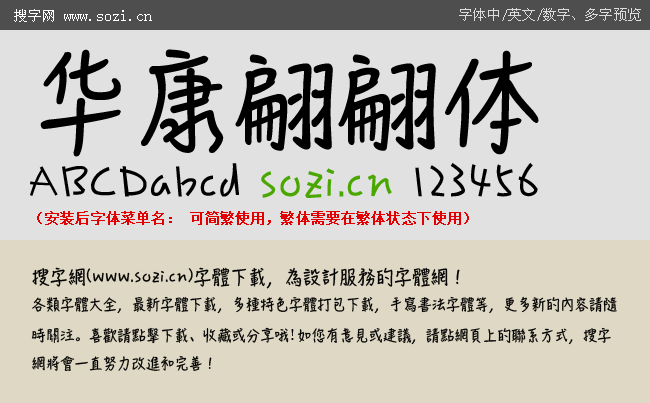
華康翩翩體
搜字網(wǎng)提供一款手寫(xiě)風(fēng)格的華康翩翩體手機(jī)中文字體下載。華康翩翩體是一款硬筆風(fēng)格的書(shū)法字體,字呈長(zhǎng)型,右上揚(yáng)起,清秀灑脫,筆觸帶著俏皮的律動(dòng)感,整體活潑生動(dòng),呈現(xiàn)自然手感,是一套親和隨興的手寫(xiě)字體。喜歡書(shū)法的朋友快快下載吧。